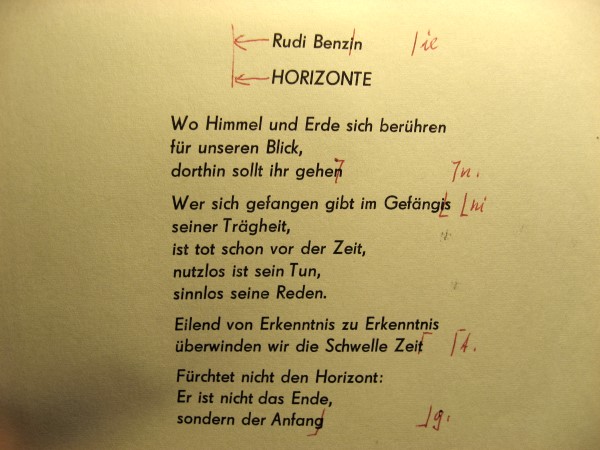
kursive Serifenlose sind überflüssig.
Das habe ich so verstanden, dass es sich ausschließlich um das @-Zeichen dreht , das in serifenloser kursiver Form überflüssig ist, und nicht um die Schriftart als ganzes.
Meinst du, wir Bleisetzer können mit Aufträgen für zweisprachige Fahrpläne rechnen? Fänd ich ja nicht übel, da könnte man sich eine goldene Nase verdienen. Dann denke ich natürlich noch mal nach über die Investition in kursive Serifenlose.
Danke für die wortreiche Antwort, Martin! Ein kurzes »nein, aber für meine Arbeit brauche ich sie nicht« hätte meine Frage übrigens auch beantwortet. ;-)
Ich bin, ganz ernsthaft, aber froh, dass du kursive Schnitte serifenloser Schriften zumindest für die von mir erwähnten Anwendungen anscheinend nicht komplett ablehnst. Es wäre ja schade, wenn Museumsbesucher, Fahrplanleser  und Leitsystemfolger sich von einer empfundenen Falschheit solcher Anwendungen vom Inhalt ablenken ließen.
Mit anderen Worten: Kursive Serifenlose sind doch nicht überflüssig, sobald man Deine kleine Welt verlässt. Es klang nur zuerst so, als wäre das als allgemein gültige Aussage gemeint.
(Ganz unter uns: Kein Mensch braucht kursive Serifenlose. Das darf man aber nicht denken, geschweige sagen. Es ist schwierig mit der Meinungsfreiheit, besonders im Design. Da geht es um Anpassung.)
Das habe ich so verstanden, dass es sich ausschließlich um das @-Zeichen dreht , das in serifenloser kursiver Form überflüssig ist, und nicht um die Schriftart als ganzes.
(Unter uns: Pst! Doch.)
Danke für die wortreiche Antwort, Martin! Ein kurzes »nein, aber für meine Arbeit brauche ich sie nicht« hätte meine Frage übrigens auch beantwortet. ;-)
Ich bin, ganz ernsthaft, aber froh, dass du kursive Schnitte serifenloser Schriften zumindest für die von mir erwähnten Anwendungen anscheinend nicht komplett ablehnst. Es wäre ja schade, wenn Museumsbesucher, Fahrplanleser  und Leitsystemfolger sich von einer empfundenen Falschheit solcher Anwendungen vom Inhalt ablenken ließen.
Auch ernsthaft: In diesem Thread geht es bislang um nichts anderes als Bleisatz. Darauf habe ich mich natürlich vor allem bezogen. Bis ein Akzidenzsetzer sich eine kursive serifenlose Bleischrift kauft und aufstellt und danach sogar auf immer darüber hinaus, müßte er diese Investition und diesen Raum, auf dem das Schriftregal steht, mit anderen Schriften finanzieren, die viel häufiger gebraucht werden. Ich weiß gar nicht, wann es die ersten kursiven Serifenlosen in den Druckereien gab. Ich würde vermuten, daß sie die letzte Schriftgattung sind. 20. Jahrhundert? Bei Druckereiauflösungen, von denen ich nun schon etliche erlebt habe, sah ich sie selten. Ich hab eben mal im Bleisatzmagazin Rheinland in den Bestand geschaut: von 52 Serifenlosen sind zwei schräg oder kursiv. (Und das liegt nicht daran, daß die gleich weggekauft würden, im Gegenteil, die will auch kaum jemand haben.)
Beim kursiven @ als typungebundener Bleiletter hätte man überdies mit dem Problem zu kämpfen, daß es wahrscheinlich zu keiner Kursiven paßt wegen der unterschiedlichen Neigungen.
Und dann: Kursive Serifenlose verarbeite ich so gut wie nie; für meine Arbeit erscheinen sie mir überflüssig, und ich kann mich nicht erinnern, mich als Leser an einer erfreut zu haben. Auch Serifenlose bereiten mir nicht die Freude wie die komplexeren Formen aller anderen Arten von Schriften, wenn ich damit arbeite oder sie mir in einem schönen Werk ansehe. Als Leser halte ich die Serifenlosen oft für eine Pest. Inhaltsangaben auf Lebensmittelpackungen in 4 Punkt schmalmager, weiß auf hellbraun gedruckt. Mit einer Serifenlosen geht das, deshalb wird es gemacht. Lesen kann es niemand. Auf dem Bildschirm in 400% sah es okay aus. Allzu oft geben sie ein furchtbar fades Bild. Sie sind an sich spannungsarme Schnurzugwürmer, und sie gut zu setzen, so daß sie schön aussehen, macht viel mehr Arbeit als der Satz einer lebendigeren Schrift. Man muß sich nur einmal Hinweistafeln von Gerwerbegebieten anschauen. Die meisten Schilder sind aus Serifenlosen gesetzt. Ein trostloses Bild. Sie korrespondieren in ihrer platten Plakativität auch oft mit dem Text. Ich bin mit Propaganda aufgewachsen. Weiße Schrift auf roten Bannern: Betrieb der ausgezeichneten Qualitätsarbeit. Vorwärts zum xten Parteitag der SED. Wie würde denn das in einer kursiven Caslon mit Zierversalien auch aussehen. Lächerlich natürlich. Die fette Serifenlose hat etwas Bedrohliches, die schlägt dich tot, walzt dich nieder, wenn du nicht mitmarschierst. Die ist nicht sonderlich feinsinnig oder geistvoll.
In Schriftmischungen kann man natürlich mit einer Versalzeile einer serifenlosen Art-déco-Type eine schöne ornamentale Linie herstellen, beispielsweise. Aber wer macht das schon auf einem Schild für ein Gewerbegebiet. Das darf ja nichts kosten, das macht der Schilderfritze in zehn Minuten. Und im Kundengespräch meinen alle übereinstimmend irrend: zeitgemäß ist serifenlos. Es gibt auch ganz irre superfette Serifenlose mit wunderschönen Formen. Das gemeine i aus der Gill Sans Nova Ultra Bold: phantastisch! (Übrigens sind Extra und Ultra Bold nicht kursiv gezeichnet worden.) Aber wo setzt man das schon ein.
Kursbücher und so etwas sind nicht mein Gebiet, damit kenne ich mich nicht aus. Ich entwerfe persönliche Drucksachen und Bücher, und das ist natürlich eine sehr subjektive Arbeit, so sehr man dagegen ankämpft. Ich löse nicht die Probleme, die ein Typograf mit einer anderen Auftragsstruktur lösen muß. Meine Welt ist wirklich klein, und es geht in ihr immer nur um die passende Schönheit. Das beschäftigt mich, und dabei kommen kursive Serifenlose nur vor, wenn sie so komplex sind wie die extrafetten oben genannten. Oder auch als feines Initial mit einer eleganten Form. Aber für Text eher nicht. Mehrsprachige Publikationen gab es übrigens auch schon, bevor es serifenlose Schriften gab. Also zwingend ist der Einsatz von kursiven Serifenlosen sicherlich nicht. Es gibt immer mehrere Lösungen, und wenn man einen Entwurf macht, der von der kühlen Sachlichkeit oder auch scheinbaren Geometrie der Serifenlosen zehrt, warum sollte man das ohne Not mit einer kursiven zerstören? Es gibt schließlich noch viele andere Entwurfsmittel.
In ein- und demselben Beitrag sagst Du einmal, es gehe doch um die ganze Schriftgattung der kursiven Serifenlosen (auch wenn man nicht sagen dürfe, dass sie überflüssig seien – Blödsinn, natürlich darf man das sagen), und wenn die meisten Leute im Design so etwas nicht sagen, hat das wohl kaum etwas mit Anpassung zu tun, sondern damit, dass die meisten Leute dort der Meinung sind, kursive Serifenlose würden eben schon gebraucht. Und dann wieder beschränkst Du Deine Aussage auf den Bereich des Bleisatzes. Ich finde das verwirrend und widersprüchlich.
Deine rhetorisch wirkende Frage, warum man ohne Not einen Entwurf, der von der kühlen Sachlichkeit oder auch scheinbaren Geometrie der Serifenlosen zehrt, mit einer kursiven zerstören sollte (hier vermisse ich übrigens den Hinweis auf das, was man sagen oder nicht sagen darf), weil es ja schließlich noch viele andere Entwurfsmittel gebe, ist für mich nicht nachvollziehbar. Aber ich bin ja auch nur ein Laie mit ein paar autodidaktischen Kenntnissen. Wie sehen das die anderen Fachleute?
Nun mag jeder seinen eigenen Geschmack haben, was Schriften angeht. Ob nun eine serifenlose Kursive gänzlich unnötig ist, mag man sehen wie man will. Offensichtlich gab es eine Nachfrage, da diese Schriften ja bis heute angeboten werden. Ich selbst habe eine Futura Buch schräg, sogar mit lang-s und seinen diversen Ligaturen. Und auch noch die Steile Futura kursiv halbfett. Das sind sicherlich keine Brotschriften und der Einsatz im Akzidenzbereich ist sicherlich auch eher überschaubar. Für den Anzeigensatz hingegen kann ich mir schon vorstellen, dass diese Schriften dort sehr gefragt waren.